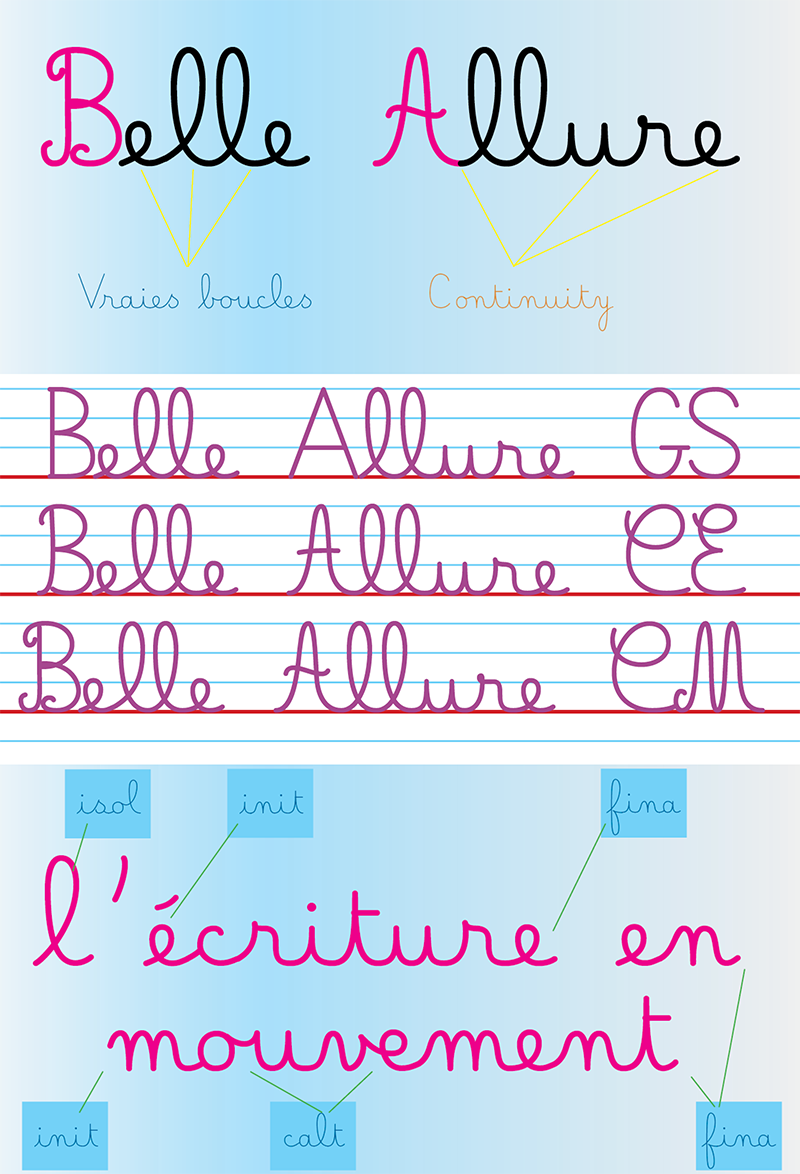
Nouvelle version : - meilleures liaisons entre les lettres (notamment après le g, j, y, z). - plus de variantes (GS, CE, CM) - des lignages intégrés (lisez le mode d’emploi). Démo réservée aux enseignants pour leur classe. Ces fontes sont conçues pour l'école primaire. Elles respectent la continuité du geste. Les e et les l sont de vraies boucles. Plus d'informations ici : http://jean.boyault.pagesperso-orange.fr/belleallure.html Pour une apparence correcte, activez les Alternatives contextuelles. For a correct look, active Contextual alternates. Demo for teachers. Commercial use : go to : http://www.myfonts.com/fonts/jbfoundry/belle-allure/ |